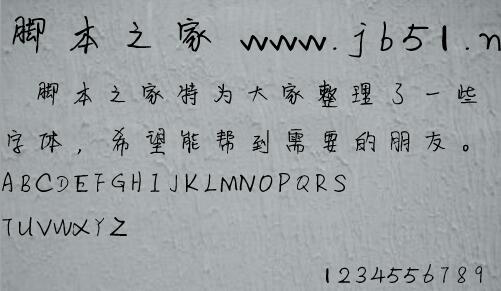
華邦喬薇硬筆行楷字體是一款很優(yōu)秀好用的藝術(shù)設(shè)計方面的硬筆行楷中文字體,該字體跟傳統(tǒng)的硬筆行楷字體有一點不同,其有著作者獨(dú)特的藝術(shù)創(chuàng)新,可以應(yīng)用于廣告海報設(shè)計,文本標(biāo)題等領(lǐng)域。歡迎喜歡這款字體的朋友下載收藏。